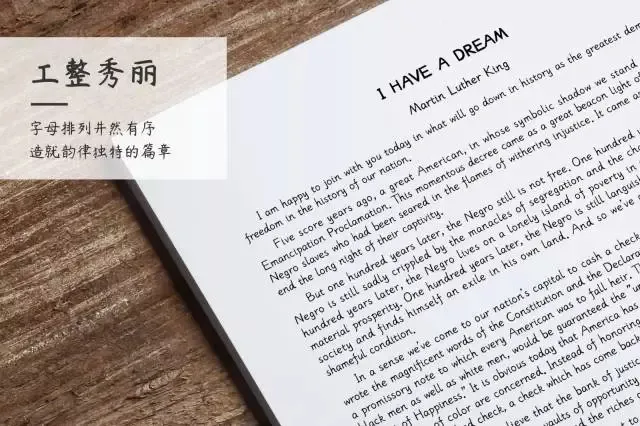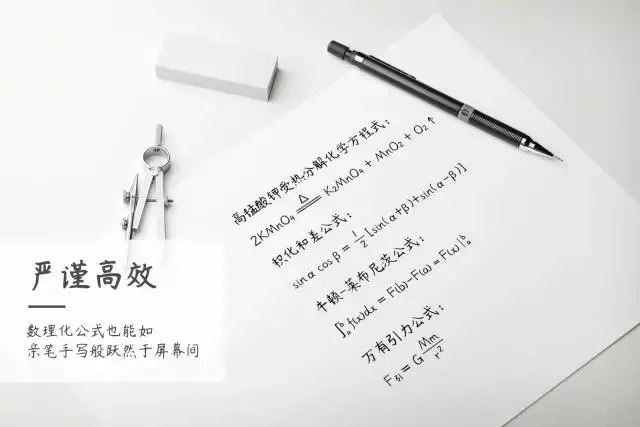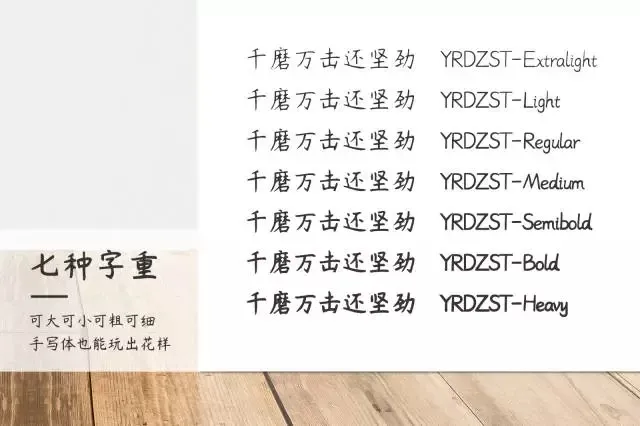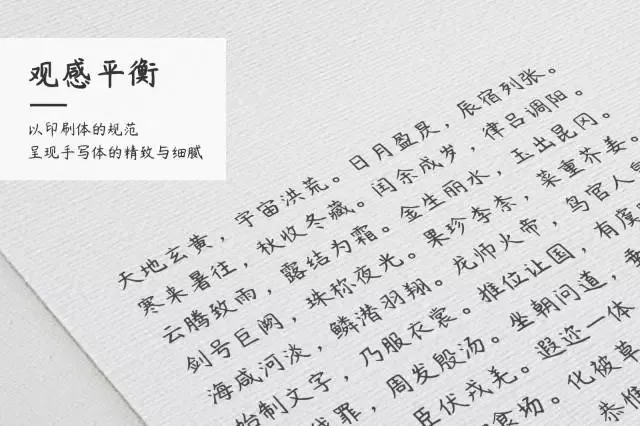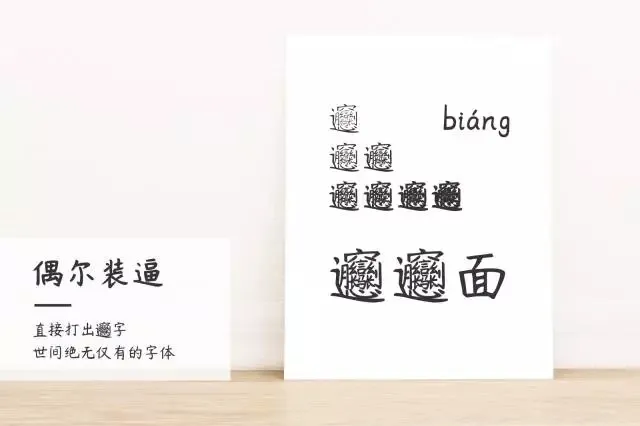
楊任東竹石體於2017年4月26日世界知識產權日正式發佈,全球首款七字重中文手寫字體,字體按照GB2312-80書寫,並增補了少量常見漢字,單個ttf格式字體文件包括7311個字符,涵蓋了日常生活用字99.8%的需求,整套字體有7個字重,共計50000餘個字符,重點是,免費可商用!
工整秀麗:字母排序井然有序,造就韻律獨特的篇章
嚴謹高效:整理化式也能和親筆手寫般躍然於屏幕間
七種字重:可大可小可粗可細,手寫體也能玩出花樣
觀感平衡:以刷體的規範,呈現手寫體的精緻與細膩
偶爾裝逼:直接打出世間絕無僅有的字